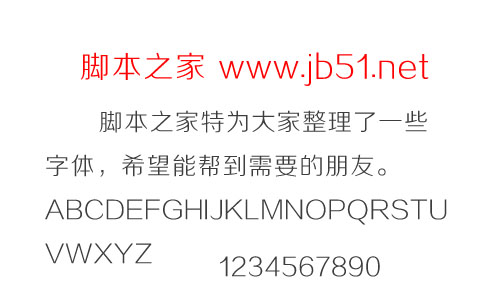
方正正纖黑簡體字體(FZZXHJW--GB1-0.ttf)是由方正字庫推出的藝術(shù)字體,該字體的字面開闊,重心較高,筆畫有對稱的鏡像感,右下角折筆處均呈圓弧形,撇捺筆畫的起筆與收筆由粗漸細(xì),正黑體取傳統(tǒng)黑體結(jié)構(gòu),筆形全部采用平行、垂直與弧度的流線形設(shè)計,簡潔易識、美觀大方,具有個性,適合書籍排版,報紙排版,海報設(shè)計,包裝設(shè)計等廣告設(shè)計場合應(yīng)用,歡迎有需要的朋友前來下載。